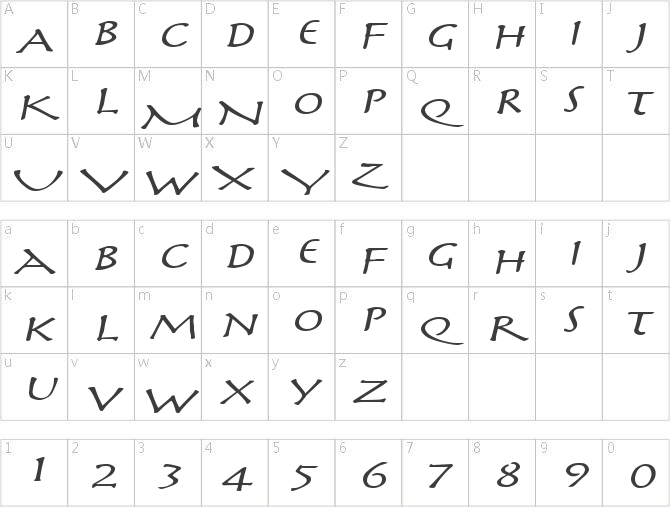
Mythology-Extended-Italic 詳情頁
Mythology-Extended-Italic字體字庫是一款讓人賞心悅目、百看不厭的英文字體,適合各類廣告和產(chǎn)品包裝設(shè)計應(yīng)用,字體大小0.07MB,格式為ttf字體,上傳用戶是Elieen,作者/版權(quán)方為未知